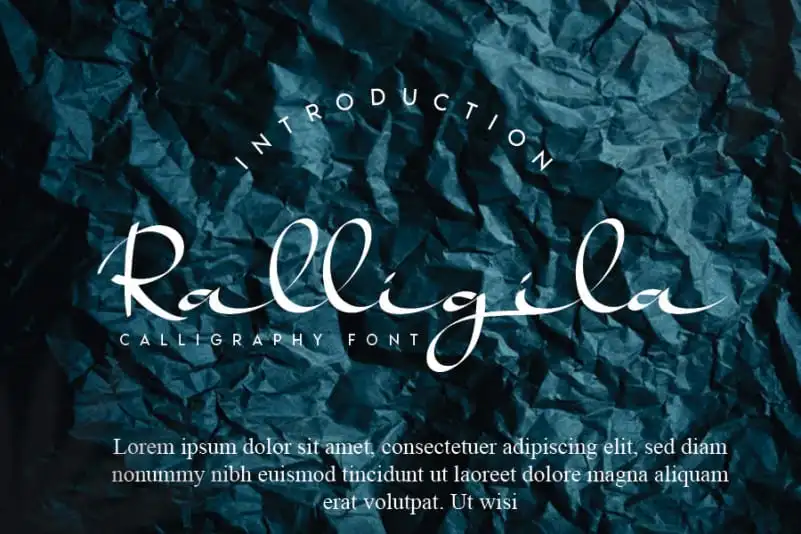
Ralligila Handwritten Font – Download Grátis
A fonte Ralligila Handwritten é uma criação inspirada nas tipografias clássicas, mas traz sua própria estética única aos projetos de design. Inspirado pela elegância das antigas tipografias, este tipo se destaca por manter influências chamuscadas enquanto evolui para um estilo contemporâneo e inovador. Perfumada com uma sensibilidade e uma frescura que vão além da mera repetição dos tempos passados, a Ralligila Handwritten é uma fonte versátil cuja variedade atrairá ideias criativas de todos os tipos. Perfeito tanto para aplicativos e cabeçalhos quanto para enfeites de papelaria, este tipo de escrever pode transformar qualquer projeto em algo único e impecável. Este design elegante é perfeito para o seu próximo projeto de design gráfico ou editoração digital.